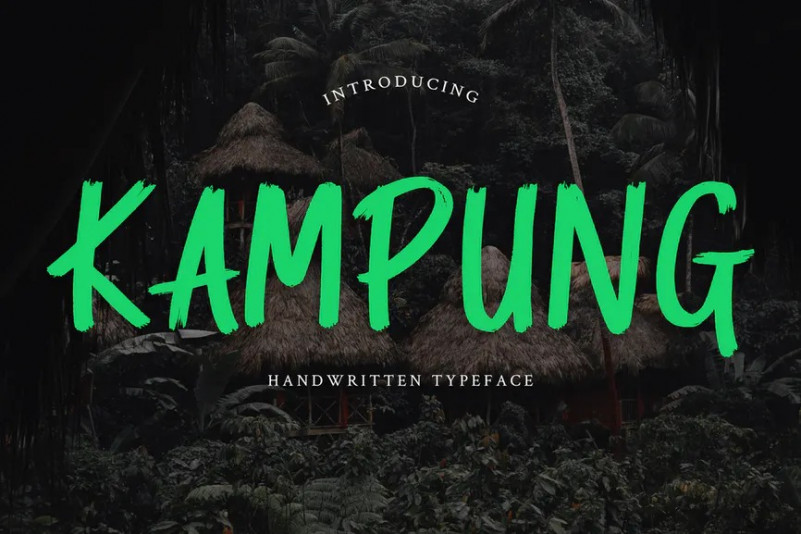
Kampung Font
Kampung est une police manuscrite au pinceau. Cette police est parfaite pour les projets de marque, Logo, couverture de livre, dessins de tshirt, messages sur les médias sociaux, publicités, emballage de produits, conceptions de produits, étiquette, filigrane, invitation, papeterie et tous les projets